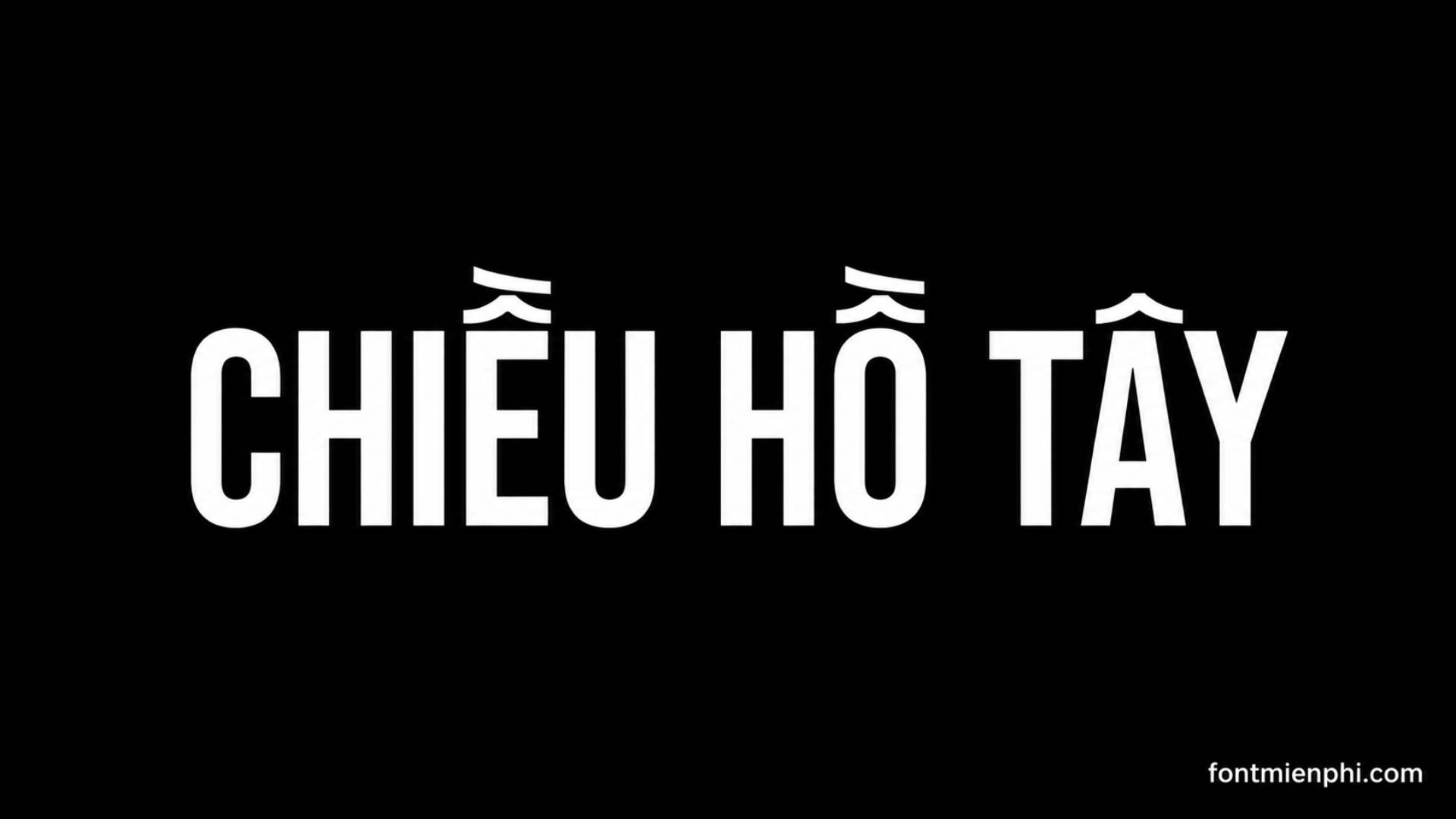
Nếu có một phông chữ xuất hiện ở khắp mọi nơi, từ các banner quảng cáo của các tập đoàn lớn, thumbnail của các YouTuber triệu sub, cho đến poster phim bom tấn Hollywood, thì đó chắc chắn là Bebas Neue. Để giúp các nhà thiết kế Việt Nam khai phá toàn bộ sức mạnh của phông chữ huyền thoại này, phiên bản Font Việt hóa PS Bebas Neue đã ra đời với bộ dấu tiếng Việt hoàn chỉnh và cực kỳ sắc nét.
1. Tổng quan về Font PS Bebas Neue
Bebas Neue ban đầu là một phông chữ dạng Sans-serif (không chân) được thiết kế bởi Ryoichi Tsunekawa. Nó nhanh chóng trở nên nổi tiếng toàn cầu và được mệnh danh là “Helvetica của dòng font Condensed” nhờ cấu trúc hình học cực kỳ cân đối và gọn gàng.
Điểm đặc trưng độc nhất của Bebas Neue là định dạng All-Caps (chỉ bao gồm chữ in hoa). Phiên bản PS Bebas Neue Việt hóa là bản tùy biến xuất sắc, giữ nguyên tỷ lệ vàng của các chữ cái gốc, đồng thời vẽ lại toàn bộ hệ thống dấu tiếng Việt theo phong cách tối giản, vuông vức để hòa hợp tuyệt đối với phông chữ.
2. Những ưu điểm vượt trội của Font PS Bebas Neue Việt Hóa
Không phải ngẫu nhiên mà trải qua nhiều năm, Bebas Neue vẫn giữ vững vị trí độc tôn trong lòng các designer. Bản Việt hóa này sở hữu những điểm cộng không thể bỏ qua:
• Sức hút thị giác mạnh mẽ: Bản chất là một phông chữ đậm nét, vươn cao, PS Bebas Neue tạo ra một điểm nhấn thị giác cực mạnh, giúp thông điệp chính của bạn nổi bật ngay lập tức.
• Tiết kiệm diện tích chiều ngang tối đa: Nhờ thiết kế theo dạng Condensed (hẹp ngang), font chữ này cho phép bạn viết những tiêu đề rất dài mà không sợ bị tràn viền hay phải thu nhỏ size chữ quá mức.
• Bộ dấu Tiếng Việt chuẩn hóa chuyên nghiệp: Khắc phục hoàn toàn lỗi nhảy font, lệch dấu hoặc các dấu thanh (sắc, huyền, hỏi, ngã, nặng) bị quá to/quá nhỏ. Mọi ký tự gõ ra đều đạt tỷ lệ hoàn hảo.
• Độ sắc nét tuyệt vời: Hiển thị cực tốt trên cả các ấn phẩm in ấn khổ lớn (Billboards, Poster) lẫn màn hình kỹ thuật số độ phân giải cao (Retina, 4K).
3. Ứng dụng thực tế của Font PS Bebas Neue trong thiết kế
Với phong cách mạnh mẽ, hiện đại và vô cùng dứt khoát, PS Bebas Neue Việt hóa là lựa chọn hàng đầu cho các dự án:
Mẹo phối Font (Typography Tip): Vì PS Bebas Neue là font in hoa dáng hẹp, hãy kết hợp nó với một font chữ nội dung (Body text) có dáng tròn, chữ thường mềm mại như Montserrat, Roboto, Open Sans hoặc Arial để tạo nên sự tương phản hoàn hảo cho bố cục.
• Thiết kế Banner Quảng cáo & Khuyến mãi: Phù hợp cho các chương trình Sale mạnh, Black Friday, hoặc các chiến dịch cần thông điệp to, rõ, giật gân.
• Làm Thumbnail YouTube & Ảnh bìa Facebook/TikTok: Giúp các nhà sáng tạo nội dung thu hút lượt click (CTR) cao nhờ tiêu đề video dễ đọc ngay cả trên màn hình điện thoại nhỏ.
• Thiết kế Poster Phim & Sự kiện: Đặc biệt thích hợp cho các chủ đề phim hành động, sự kiện thể thao, giải đấu Esport, hoặc các đêm nhạc EDM sôi động.
• Nhận diện thương hiệu (Branding): Làm logo hoặc headline cho các thương hiệu mang phong cách Streetwear, thời trang nam, năng động, cá tính hoặc ngành công nghệ, kiến trúc.